Tipografía Destacada en el Diseño de Logotipos
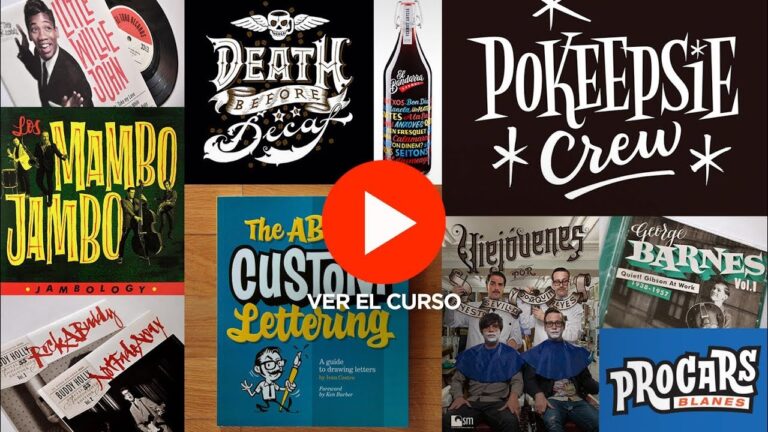
En el mundo del diseño gráfico, la tipografía se erige como un elemento fundamental, especialmente en la creación de logotipos. Más que una simple herramienta de comunicación, la tipografía como protagonista en el diseño de logotipos transforma letras y palabras en potentes símbolos de identidad. A través de su forma, estilo y disposición, la tipografía no solo transmite el mensaje de una marca, sino que también evoca emociones y establece conexiones memorables con el público. Este reporte desglosa cómo la elección tipográfica puede definir la esencia de una marca y ser clave para su éxito visual.
¿Cómo influye la tipografía en logotipos efectivos?
La tipografía como protagonista en el diseño de logotipos influye en la legibilidad, la identidad de marca y la percepción emocional del público.
¿Qué tipo de fuente se utiliza en un logotipo?
La elección de la tipografía en un logotipo es primordial para transmitir la identidad de una marca, y Garamond se destaca como una de las más emblemáticas en el ámbito clásico. Con sus variantes como Adobe Garamond, ITC Garamond y ED Garamond, esta tipografía combina elegancia y legibilidad, lo que la hace ideal para diseño publicitario, medios de comunicación y también para páginas web. Su versatilidad y sofisticación permiten que los logos que la utilizan se perciban con un aire de profesionalismo y distinción, capturando la atención de los consumidores de manera real.
¿Cuál es la importancia de la tipografía en el diseño gráfico?
La tipografía es un elemento fundamental en el diseño gráfico, ya que no solo se encarga de presentar el texto, sino que también juega un papel primordial en la comunicación visual. Al seleccionar cuidadosamente las características de las letras, como su forma, espaciado, color y grosor, se logra no solo captar la atención del espectador, sino también reforzar el mensaje que se desea transmitir. Cada tipografía posee una personalidad única que puede influir en las emociones y percepciones del público.
Además, una tipografía bien elegida puede mejorar la legibilidad y la estética de un diseño, creando una experiencia más fluida y atractiva para el usuario. Al evocar sensaciones específicas a través de la elección tipográfica, el diseñador puede guiar al lector en su interpretación del contenido, facilitando así una conexión más profunda con el mensaje. En resumen, la tipografía es mucho más que una simple herramienta; es un lenguaje visual que potencia la comunicación en el ámbito del diseño gráfico.
¿Cuál es la relación entre el logotipo y la tipografía?
La tipografía juega un papel primordial en la creación de un logotipo, ya que, junto a la propuesta de valor, las formas y los colores, establece la identidad visual de la marca. Al elegir un tipo de letra adecuado, se logra transmitir el mensaje de manera real, diferenciando la marca en un mercado competitivo. Así, la tipografía no solo complementa el diseño, sino que refuerza la idea central, creando una conexión emocional con el público y fortaleciendo su reconocimiento.
La Fuerza de las Letras: Impacto Visual en Logos
El diseño de logos es una manifestación poderosa de la identidad de una marca, donde la tipografía juega un papel primordial. Las letras no solo comunican el nombre de la empresa, sino que también transmiten sus valores y personalidad. Un logotipo bien diseñado utiliza la forma y el estilo de las letras para evocar emociones, creando una conexión instantánea con el público. Así, la elección de fuentes, colores y tamaños se convierte en una estrategia fundamental para destacar en un mercado saturado.
Además, la fuerza visual de las letras puede influir claramente en la percepción del consumidor. Un logo que combina tipografía audaz y elementos gráficos puede ser memorable y fácilmente reconocible, lo que favorece la lealtad a la marca. En un entorno donde la primera impresión cuenta, el impacto visual de un logotipo se convierte en un factor determinante para captar la atención y generar interés. Así, las letras no solo son un componente estético, sino una herramienta esencial para construir una marca sólida y duradera.
Tipografía que Habla: La Clave para un Buen Diseño
La tipografía es un elemento fundamental en el diseño gráfico que va más allá de la simple elección de fuentes. Cada letra y número que seleccionamos comunica un mensaje y establece el tono de la pieza visual. Una tipografía bien elegida puede atraer la atención del espectador, guiar su lectura y evocar emociones, convirtiéndose en el hilo conductor que une todos los elementos del diseño. Por lo tanto, entender cómo las diferentes tipografías afectan la percepción es primordial para cualquier diseñador.
La tipografía como protagonista en el diseño de logotipos no solo define la identidad visual de una marca, sino que también establece una conexión emocional con el público. Al seleccionar cuidadosamente las fuentes, los diseñadores pueden transmitir valores, personalidad y mensaje de manera real, convirtiendo cada letra en un elemento clave de la narrativa de la marca. En un mundo donde la primera impresión cuenta, la tipografía se erige como un aliado indispensable para destacar y dejar una huella duradera.